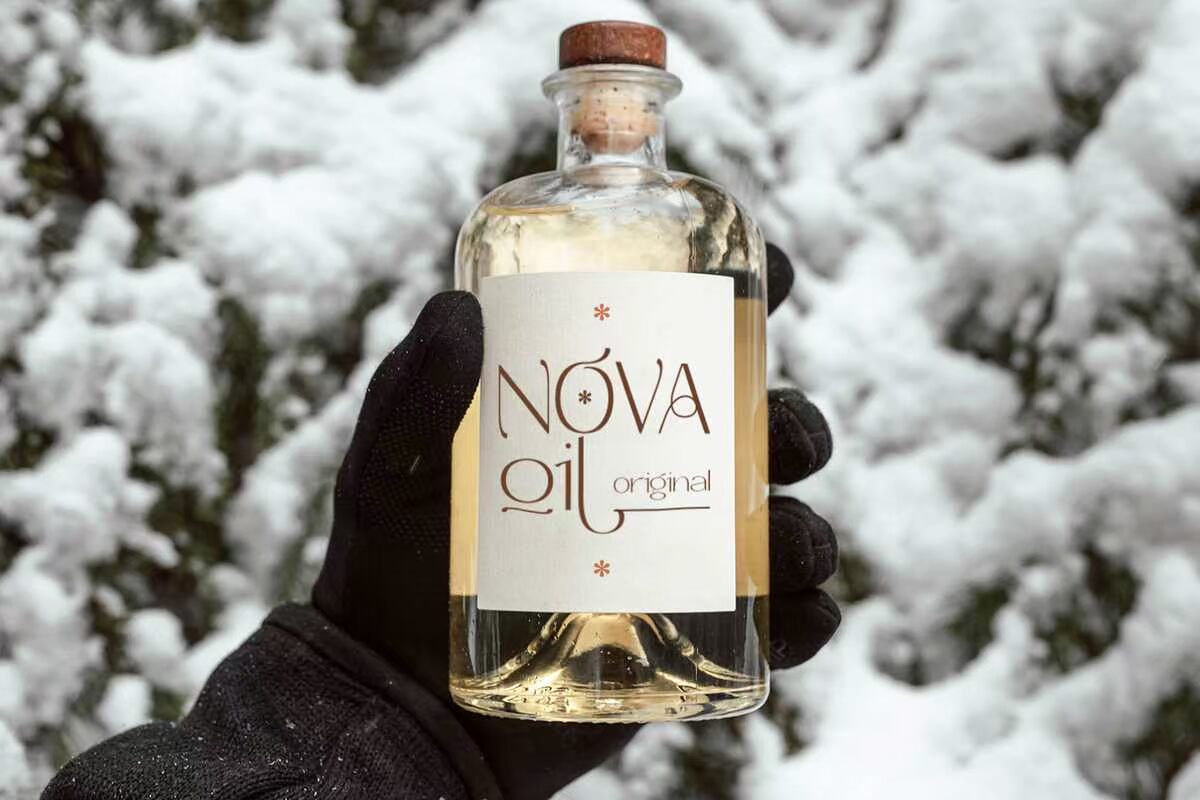
RosesBoleroElegantSansSerif是一款具有全套大写和小写字母、多语言符号、数字、标点符号和格式的Sansserif。RosesBoleroElegantSansSerif为邮政设计、杂志、,美丽的品牌,带有一个适合您美丽和美丽的设计理念的低形状立体图案。RosesBoleroElegantSansSerif是一款全套大小写字母、多语言符号、数字、标点符号和符号的Sansseriffort。RosesboleRoelegantSansseriffort古典优雅风格,适用于邮政设计、杂志、,美丽的品牌,带有一个适合您的美丽和美丽的设计理念的低形状立体图案。